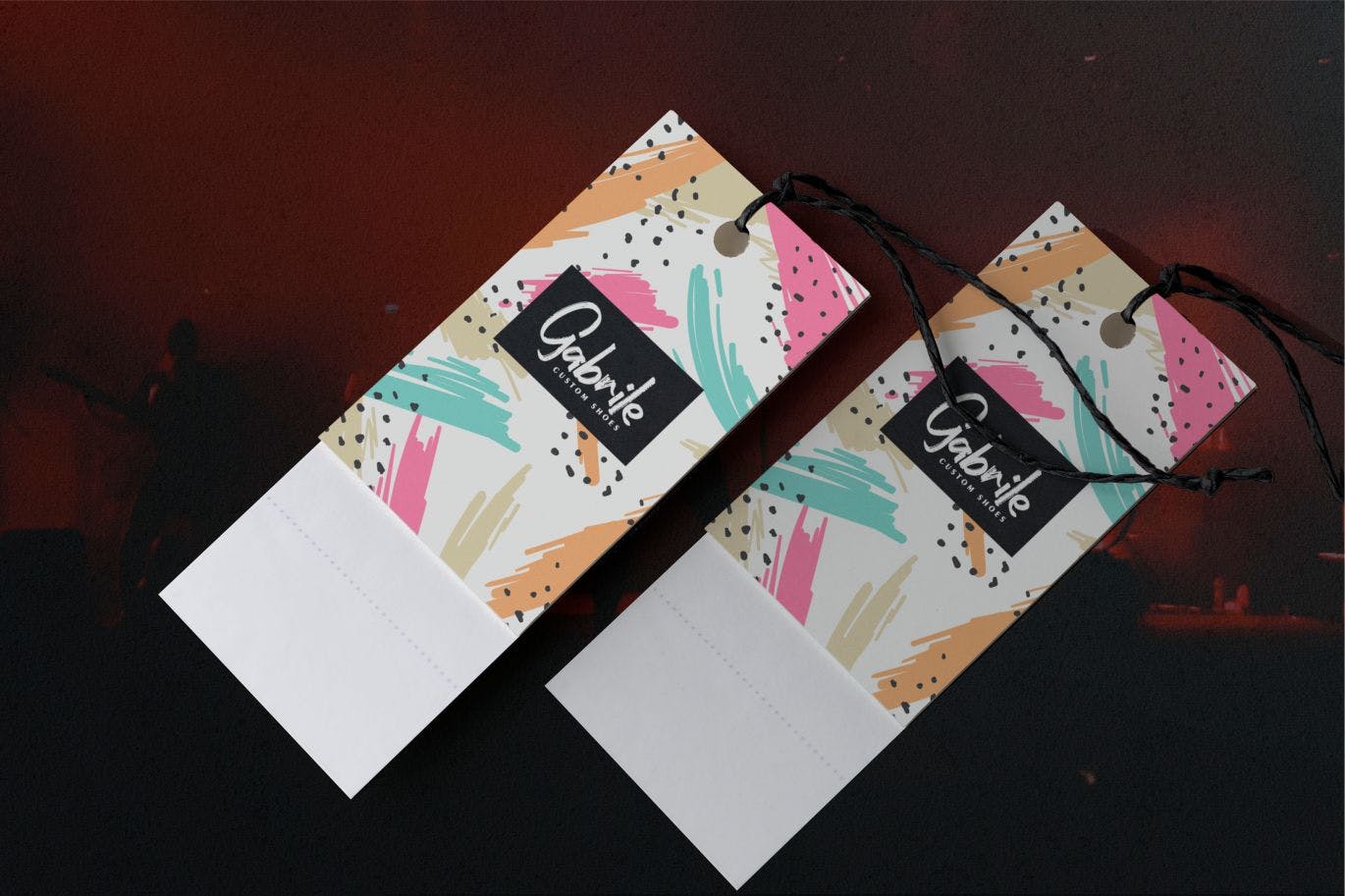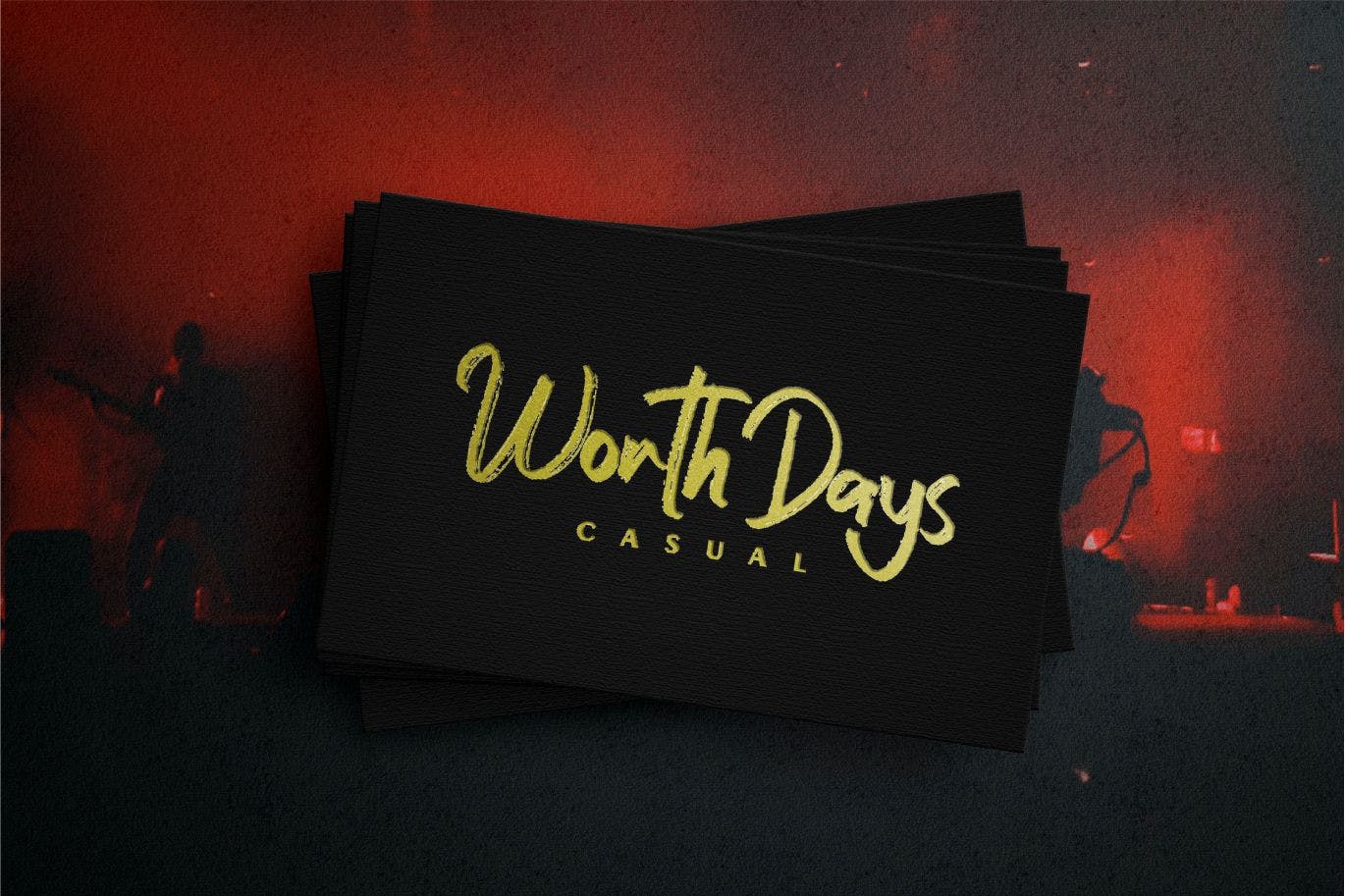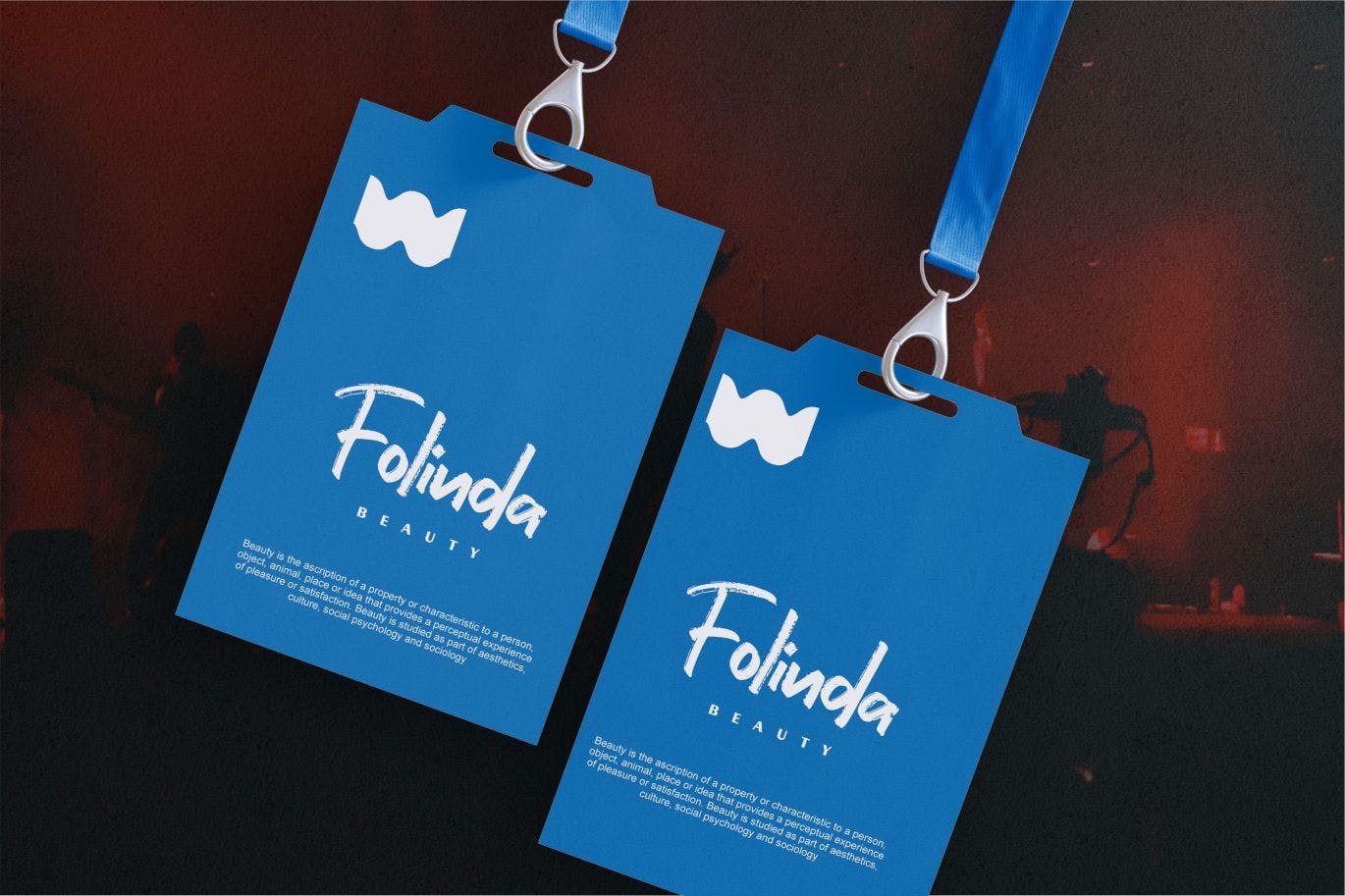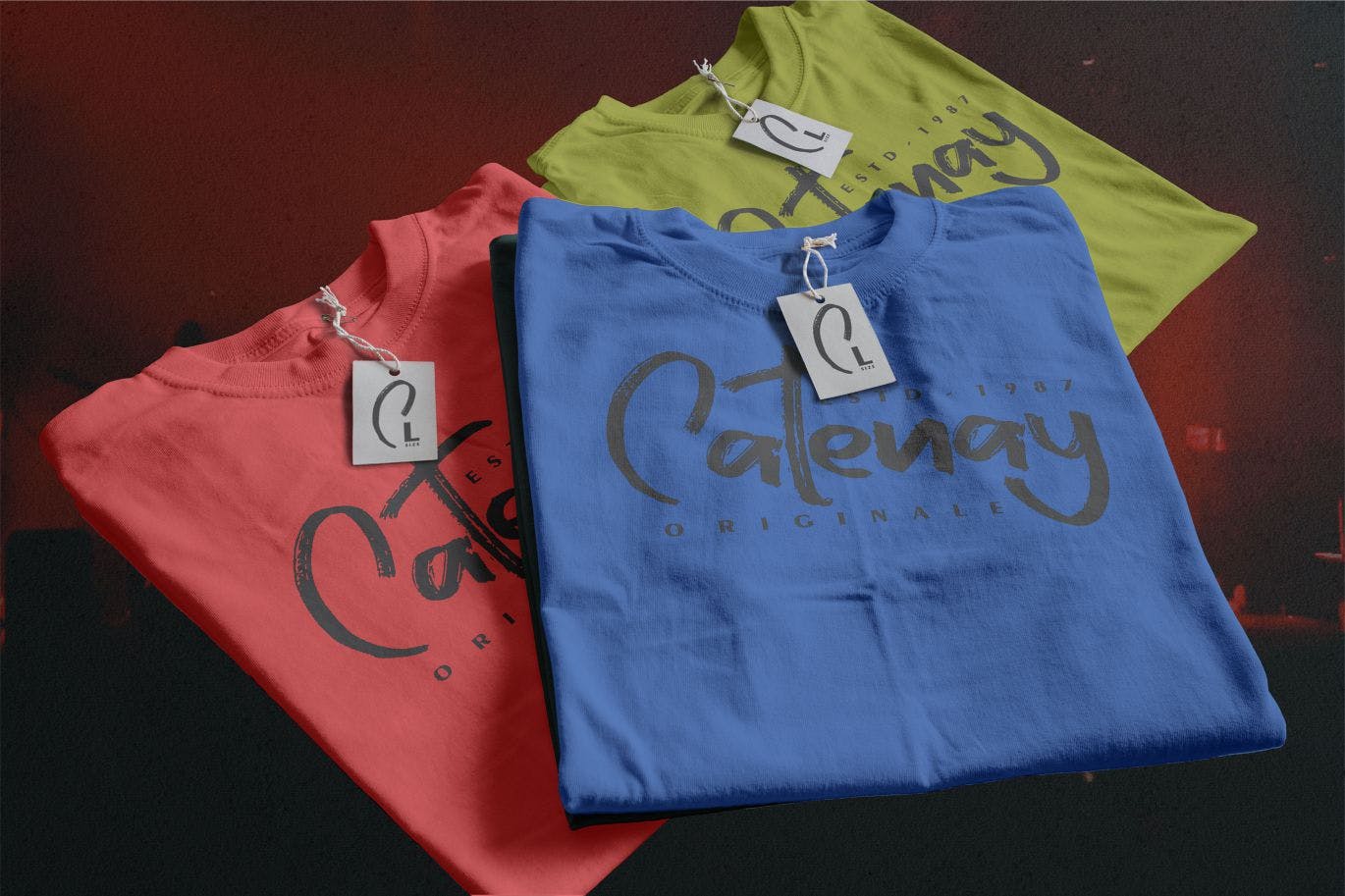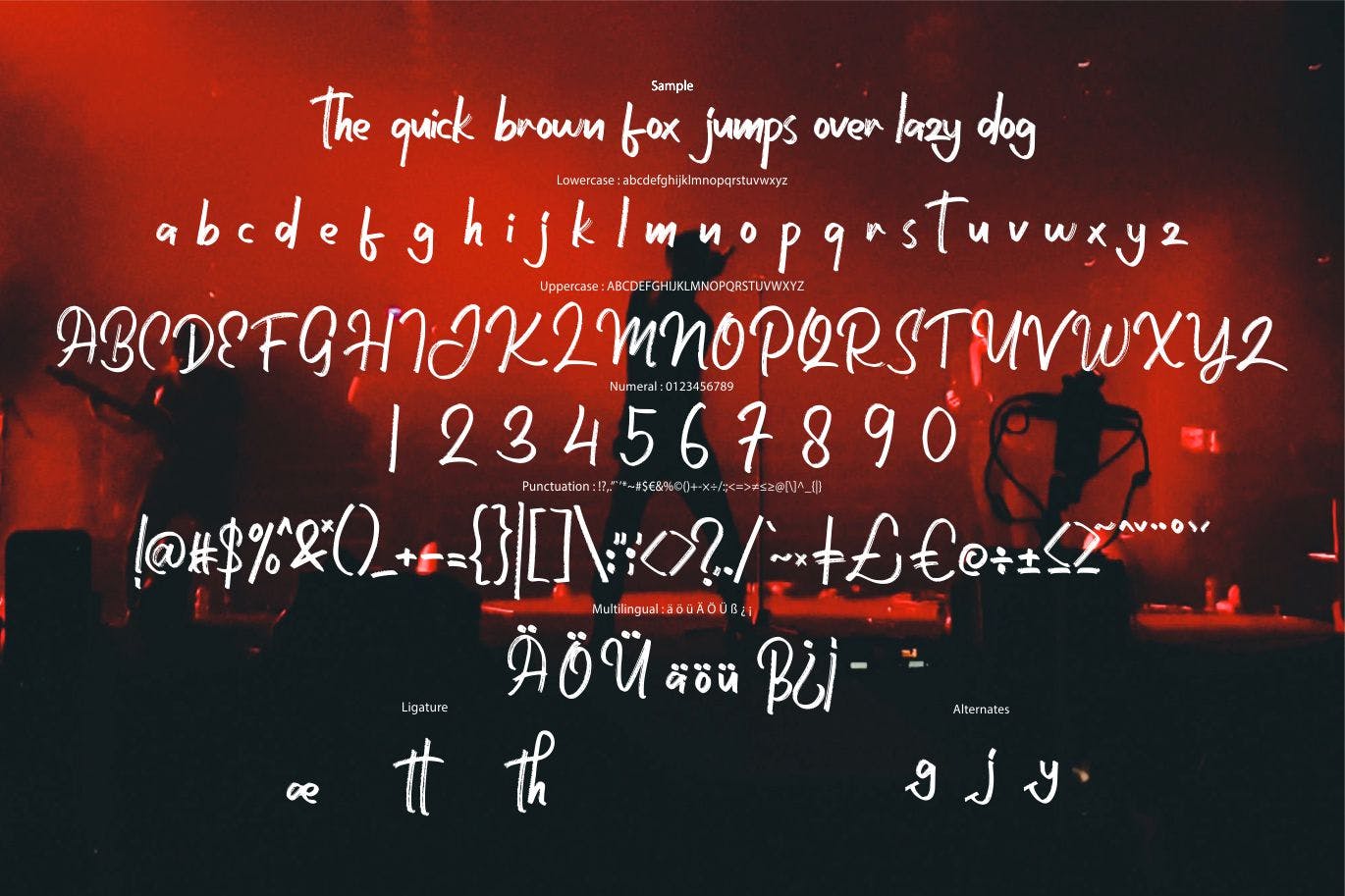
Brekad | فونت مدرن براش با سبک خوشنویسی، بسیار زیبا برای دعوتنامهها، کارتهای تبریک، مواد برندینگ، کارتهای ویزیت، نقلقولها، پوسترها و موارد دیگر مناسب است!